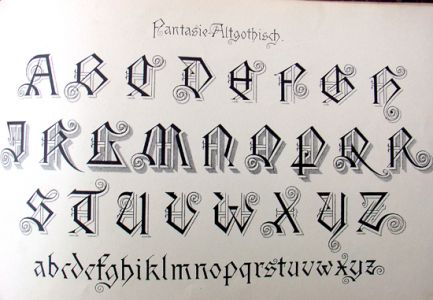
innovative, moderne Entwicklungen von Gebr. Schriften
Ein "O" wie Otto.
Meine Meinung: kranke, dekadente Schrift.
dekadent: ?
krank: auf jeden Fall!!!
»O« wie Offizin ist es leider nicht.
die Sendezeit ist leider zu Ende, hier die Auflösung (siehe Bilder).
»Wieso am Thema vorbei?«
»Es ging doch um die modernen, innovative Gebrochenen?«
»Aber auf dem Schrifmuster ist doch notiert,
IN DEN NEUESTEN FORMEN.«
»Stein alt, na gut.«
»Einschaltquote, Zwei, okay.«
»Ein für alle mal Schluß, sofort was Neues
entwickeln, okay.«
»Morgen brainstorming.«